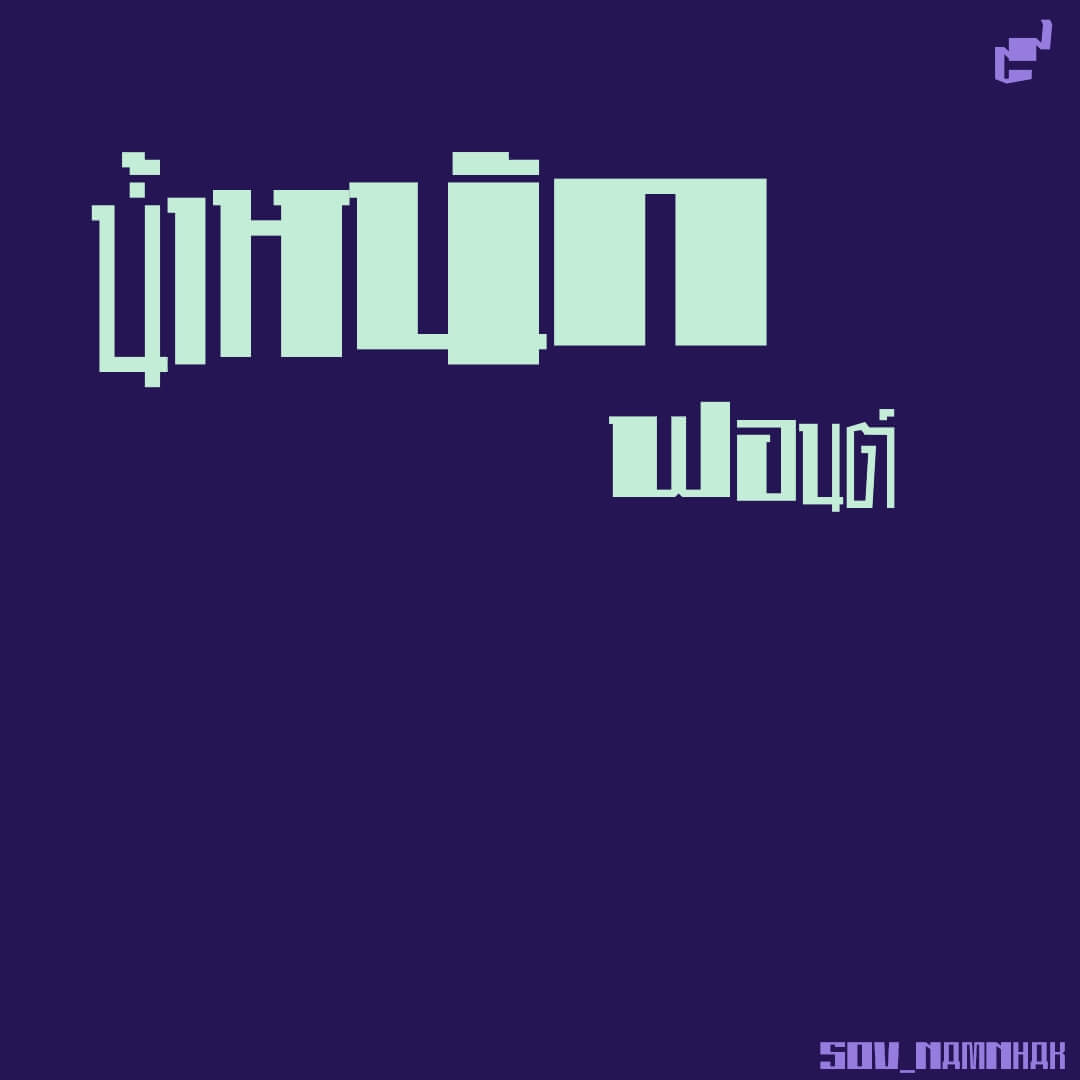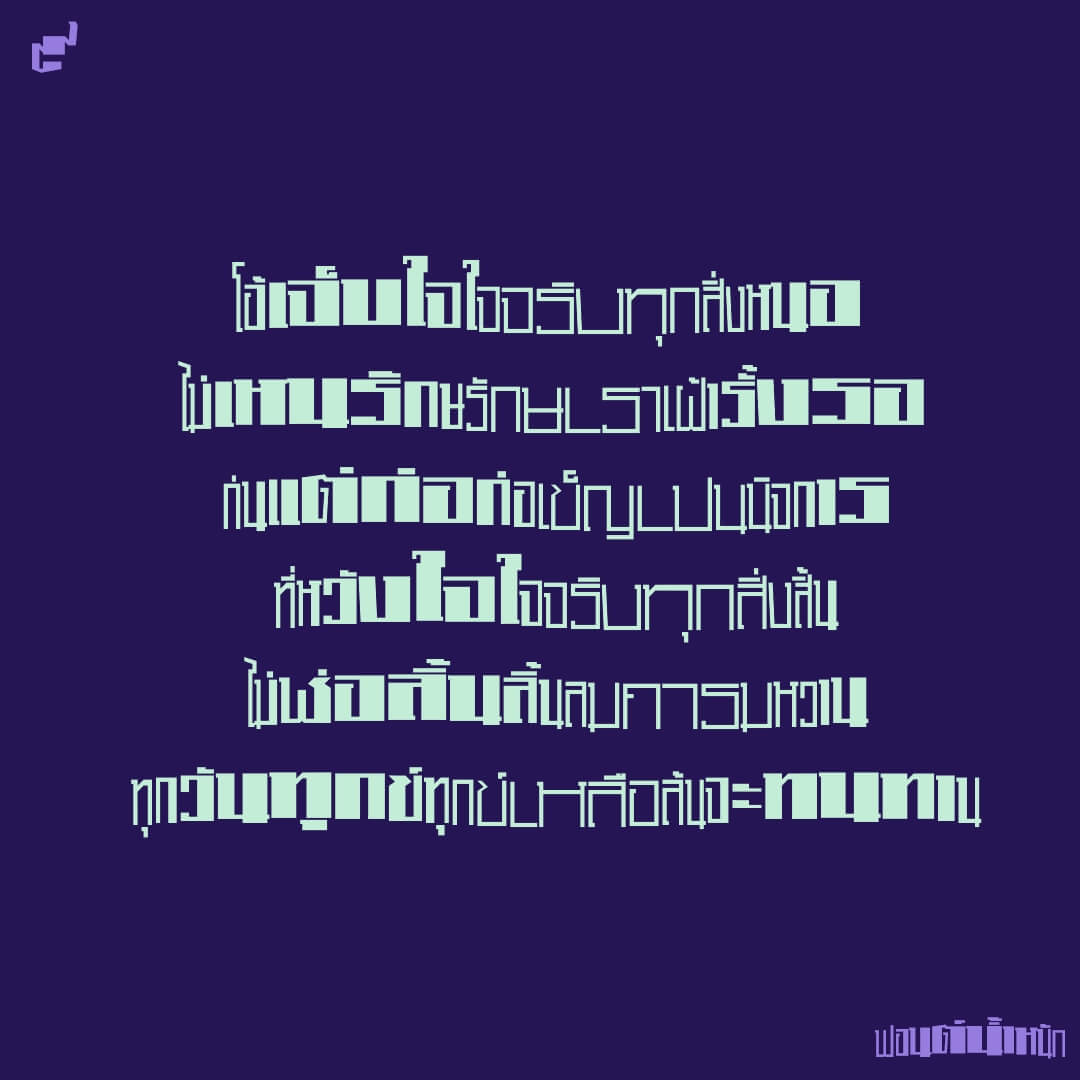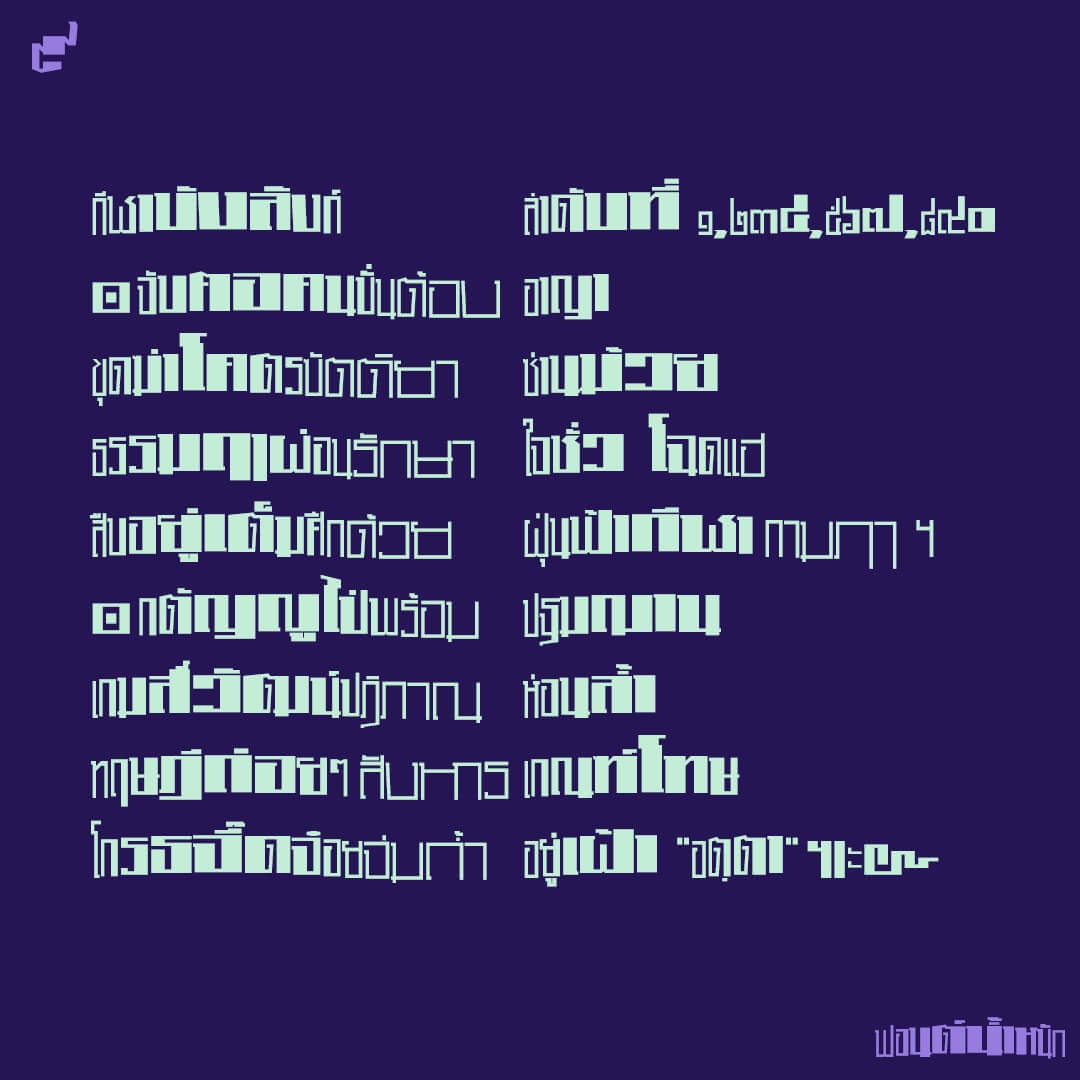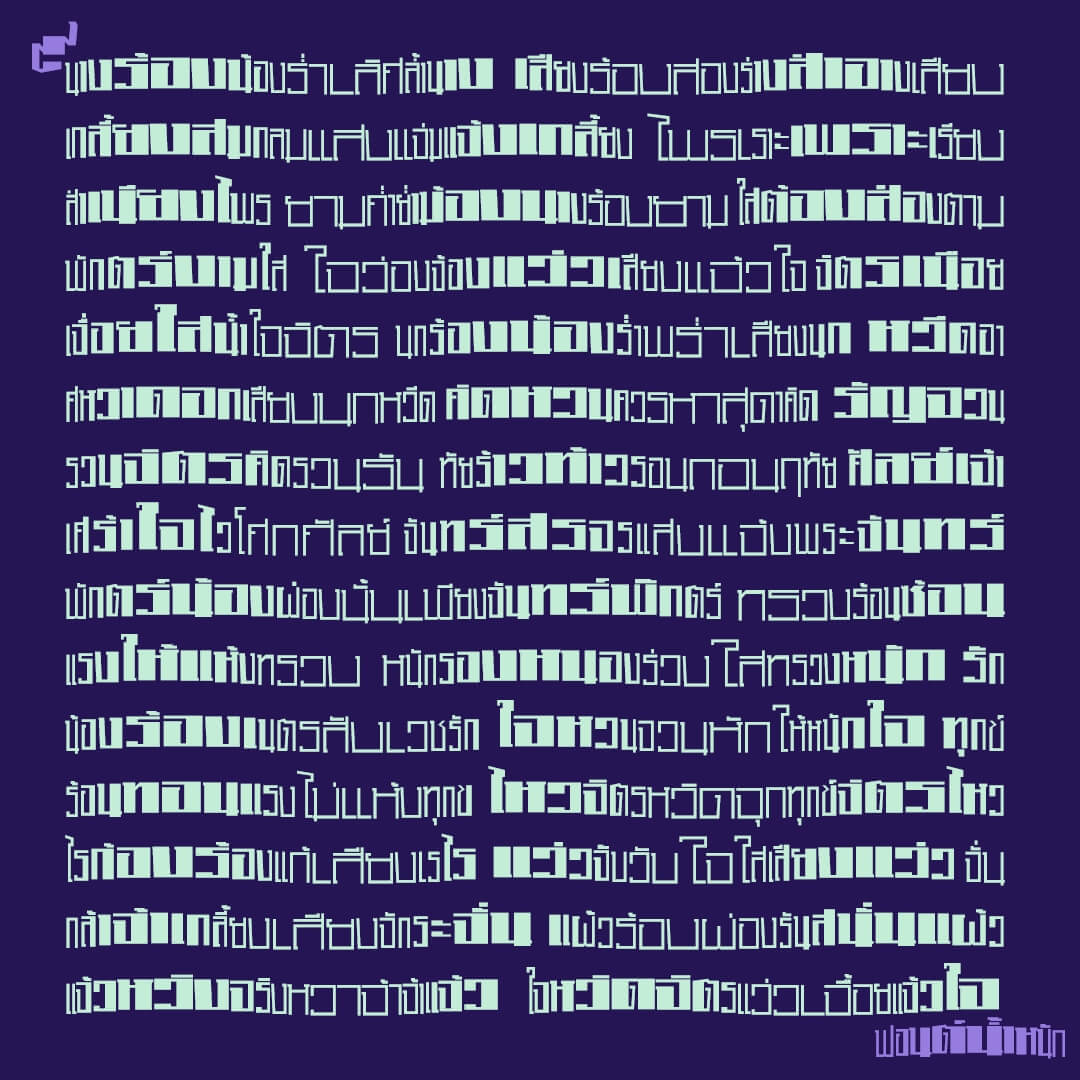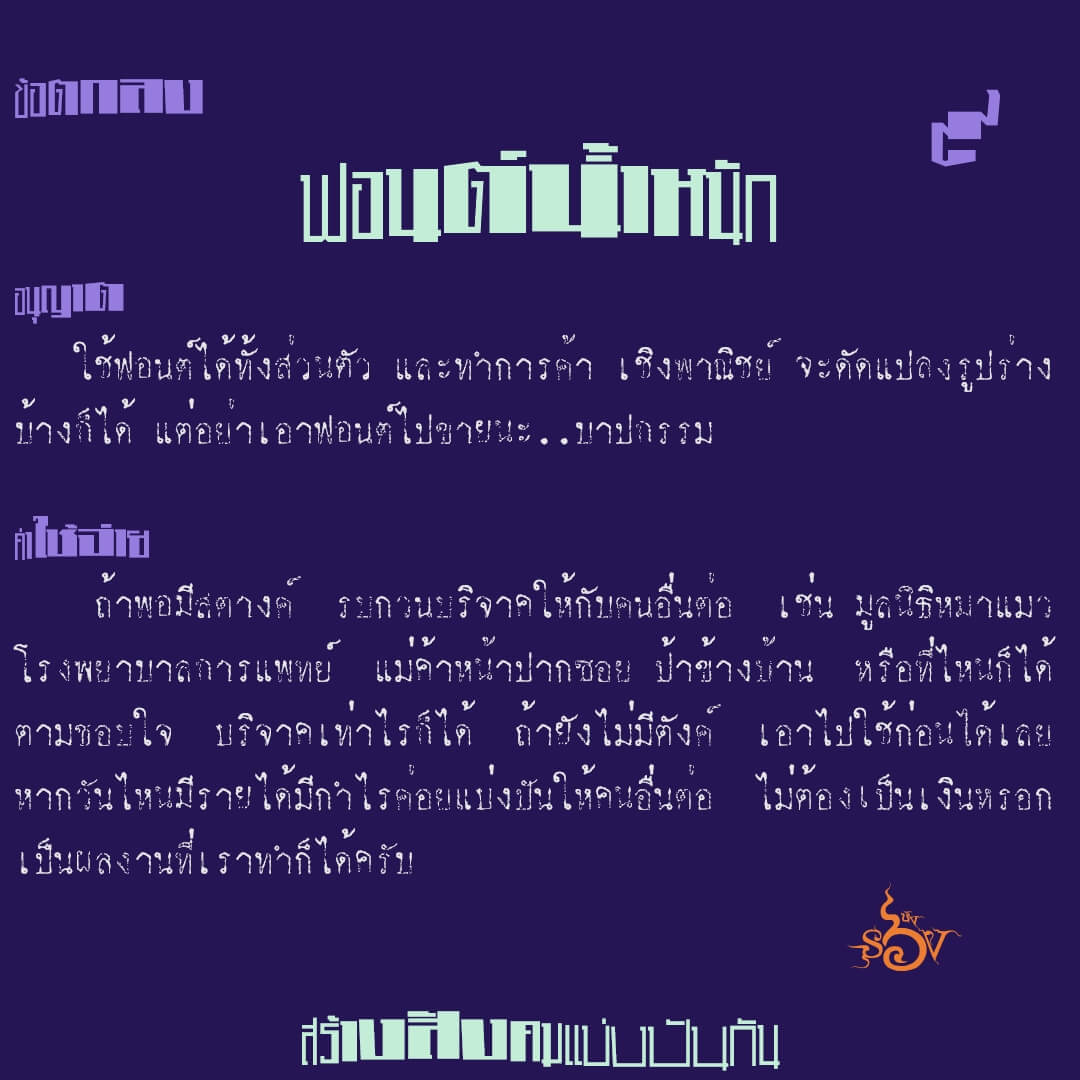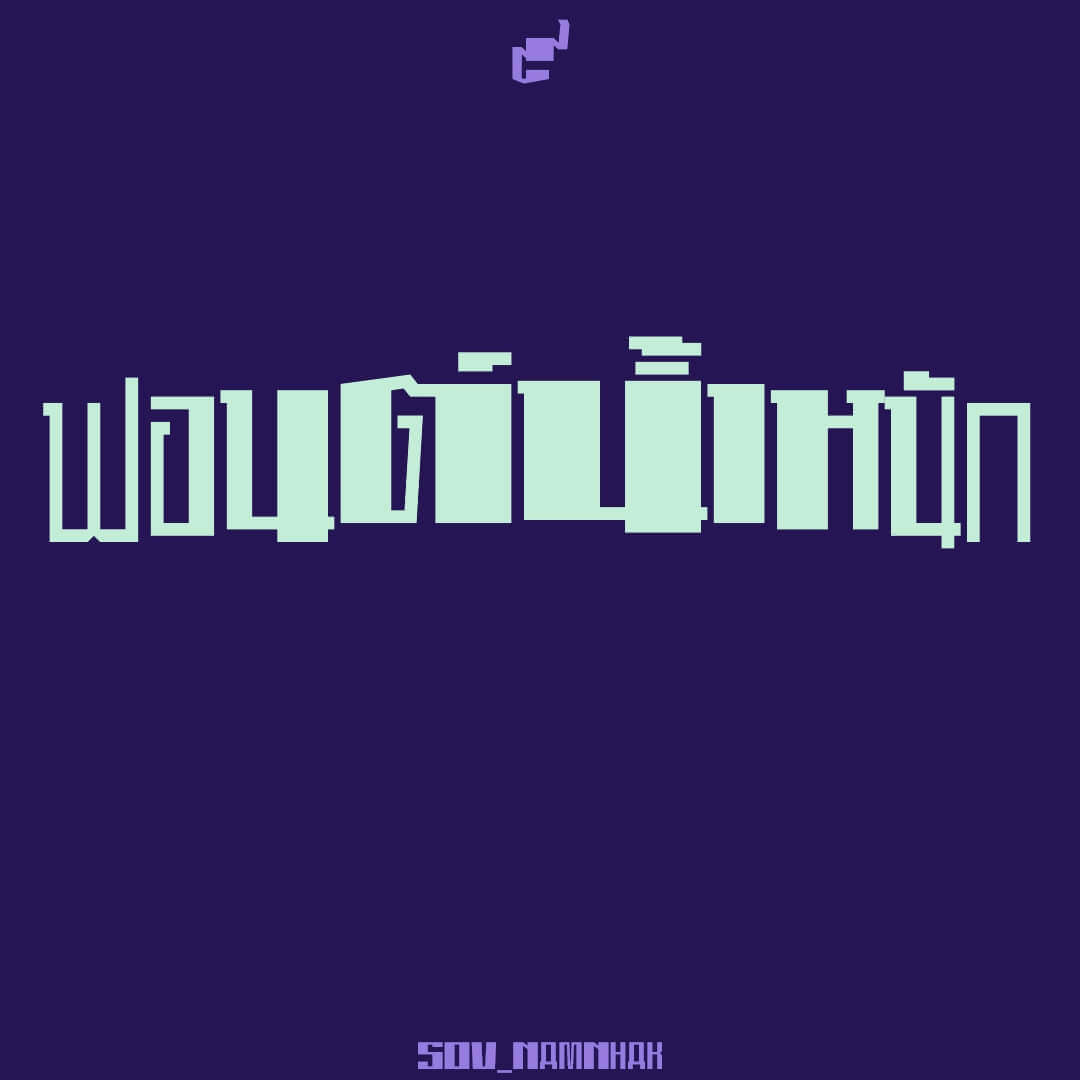
น้ำหนัก (SOV_NamNhak)
ฟอนต์น้ำหนัก – ทำอักษรวูบวาบ จากการไล่น้ำหนัก และ/หรือ ไล่ความกว้าง เหมาะใช้แค่เป็นพิ้นหลังข้อความเยอะๆ และไม่ต้องการอ่านข้อความเหล่านั้น 55 …กด bold ได้อีกแบบ